สำหรับปี 2022 มาอัปเดตฟอนต์ไทยสวย ๆ สำหรับคนที่ต้องออกแบบหรือสร้างผลงานนำเสนอในการเรียน การสอนหรือการทำงานส่วนตัวที่ไม่ใช่เชิงพาณิชย์ คัดมาไว้ให้แล้ว!
10 ฟอนต์ไทย เน้นแบบน่ารัก ๆ ฉบับอัปเดตปี 2022
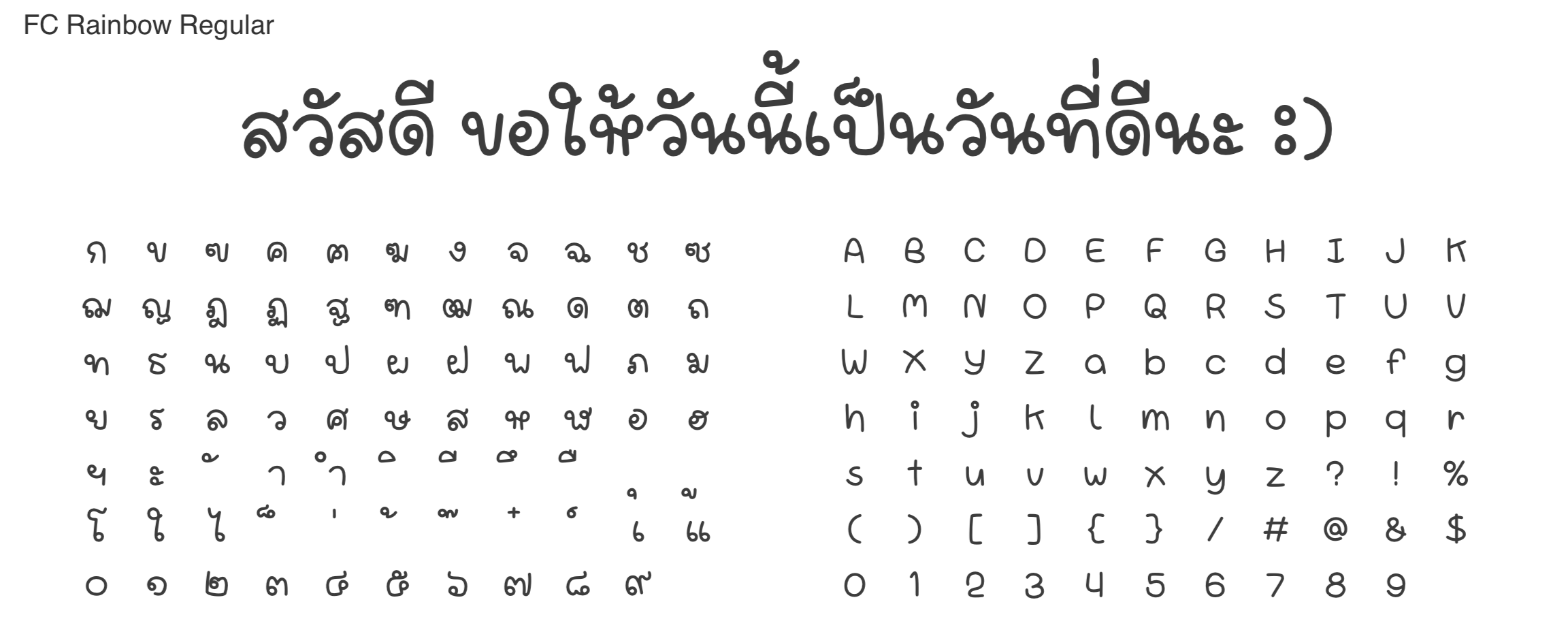
แนะนำ 10 ฟอนต์ไทยสวย ๆ สำหรับใช้งานบนคอมพิวเตอร์, iPhone และ iPad (อัปเดต 2022)
1.เอฟซี เรนโบว์ (FC Rainbow)
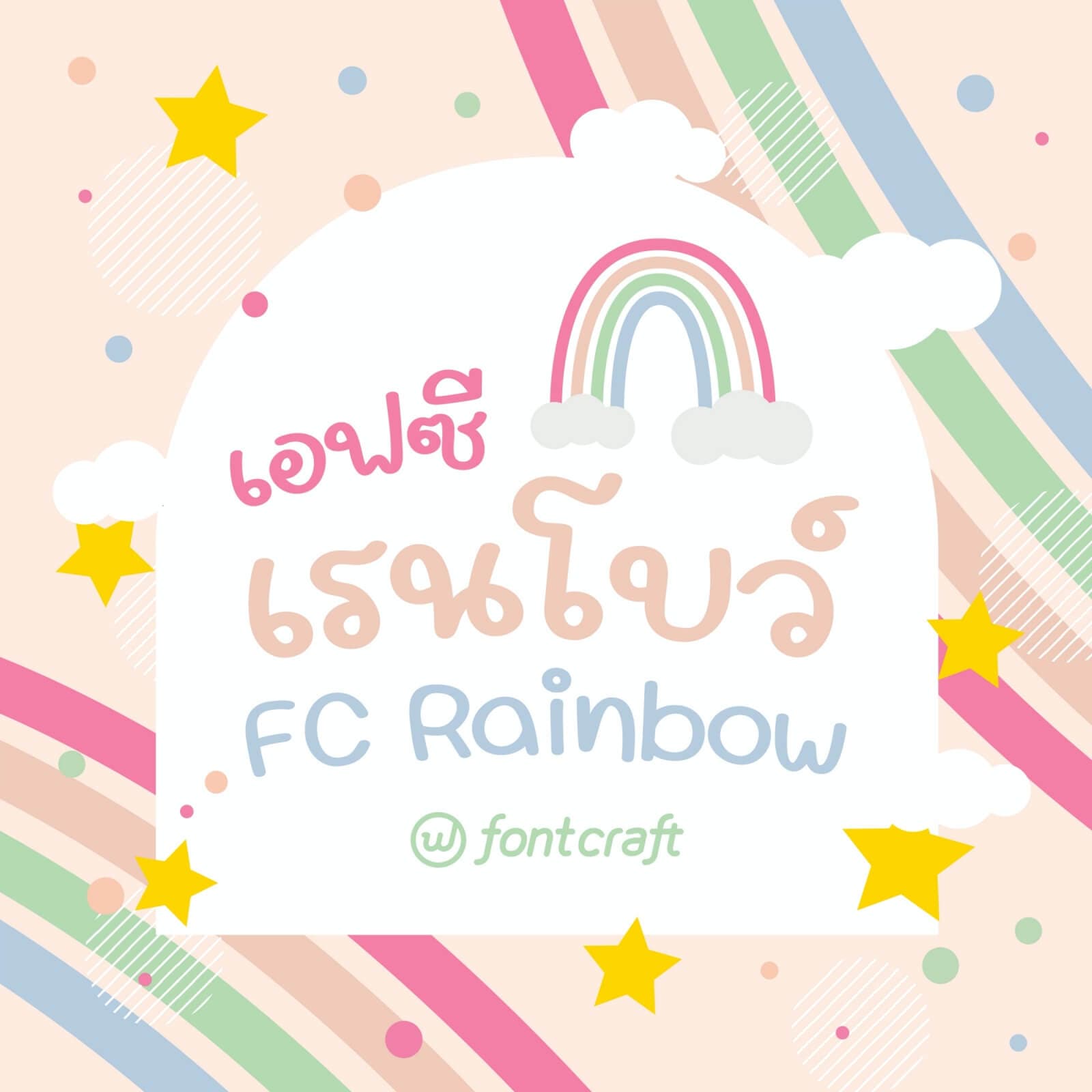
2. เอฟซี ซับเจค ราวด์ (FC Subject Rounded)
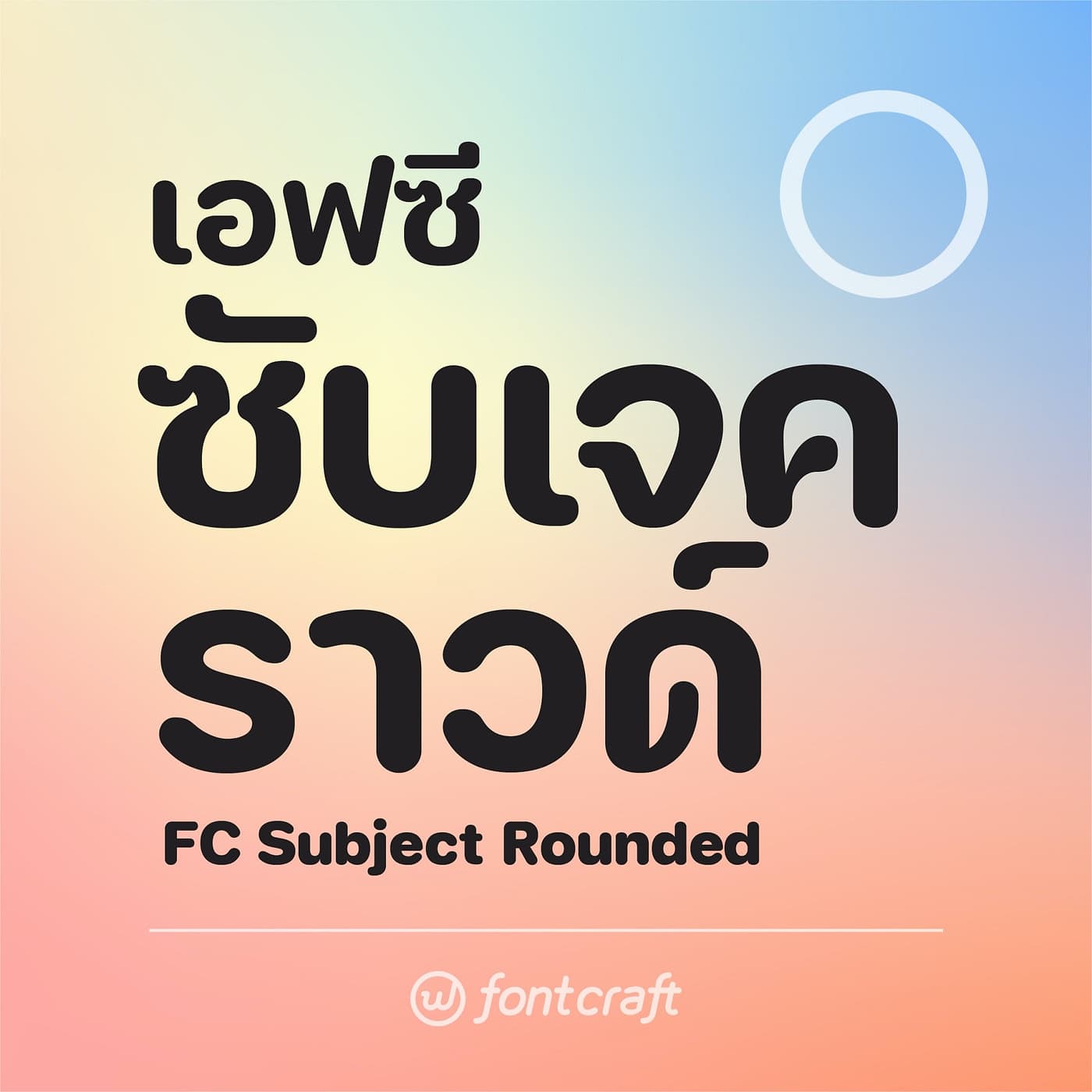
3. เอฟซี เมจิก (FC Magic)
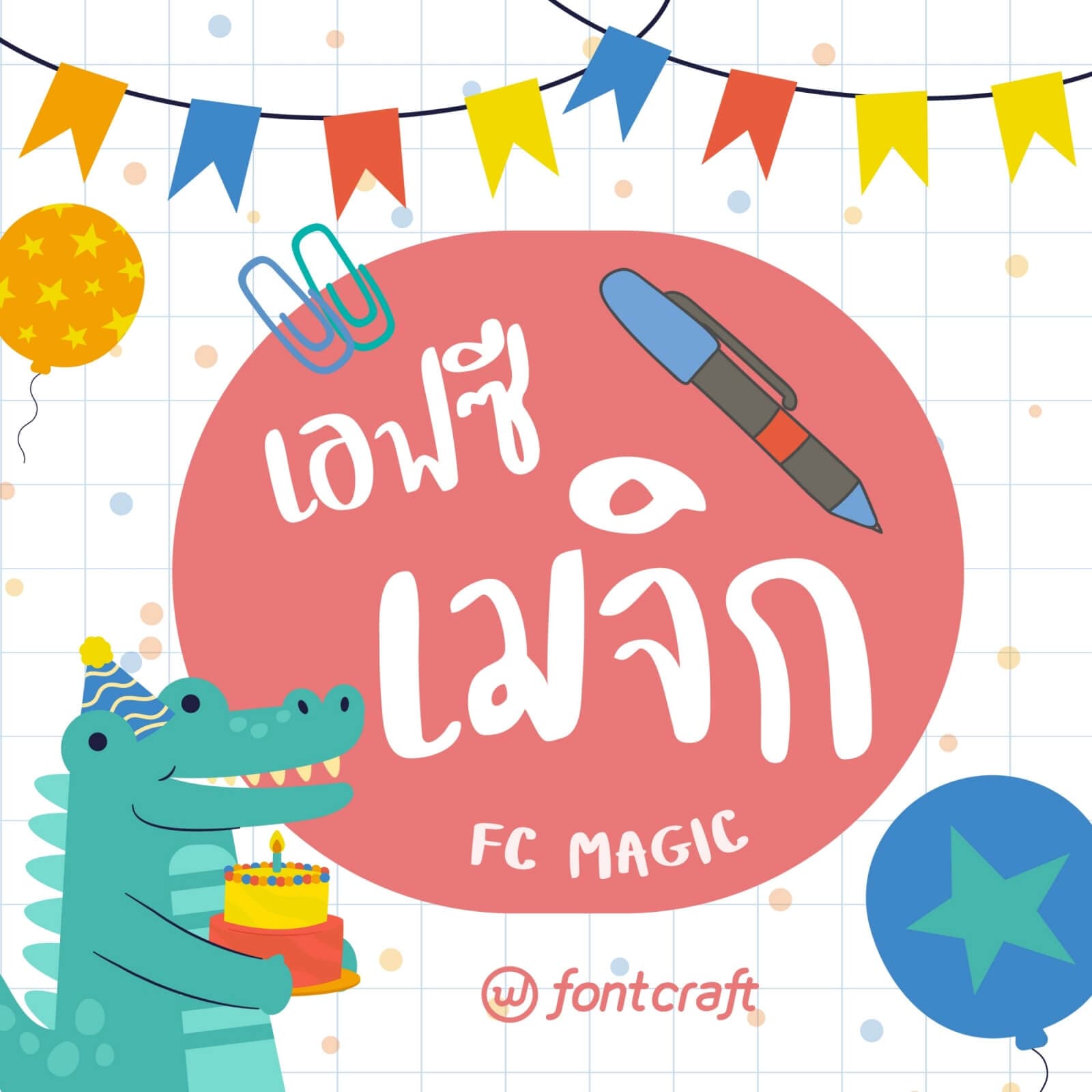
4. เอฟซี แคนดี้ (FC Candy)
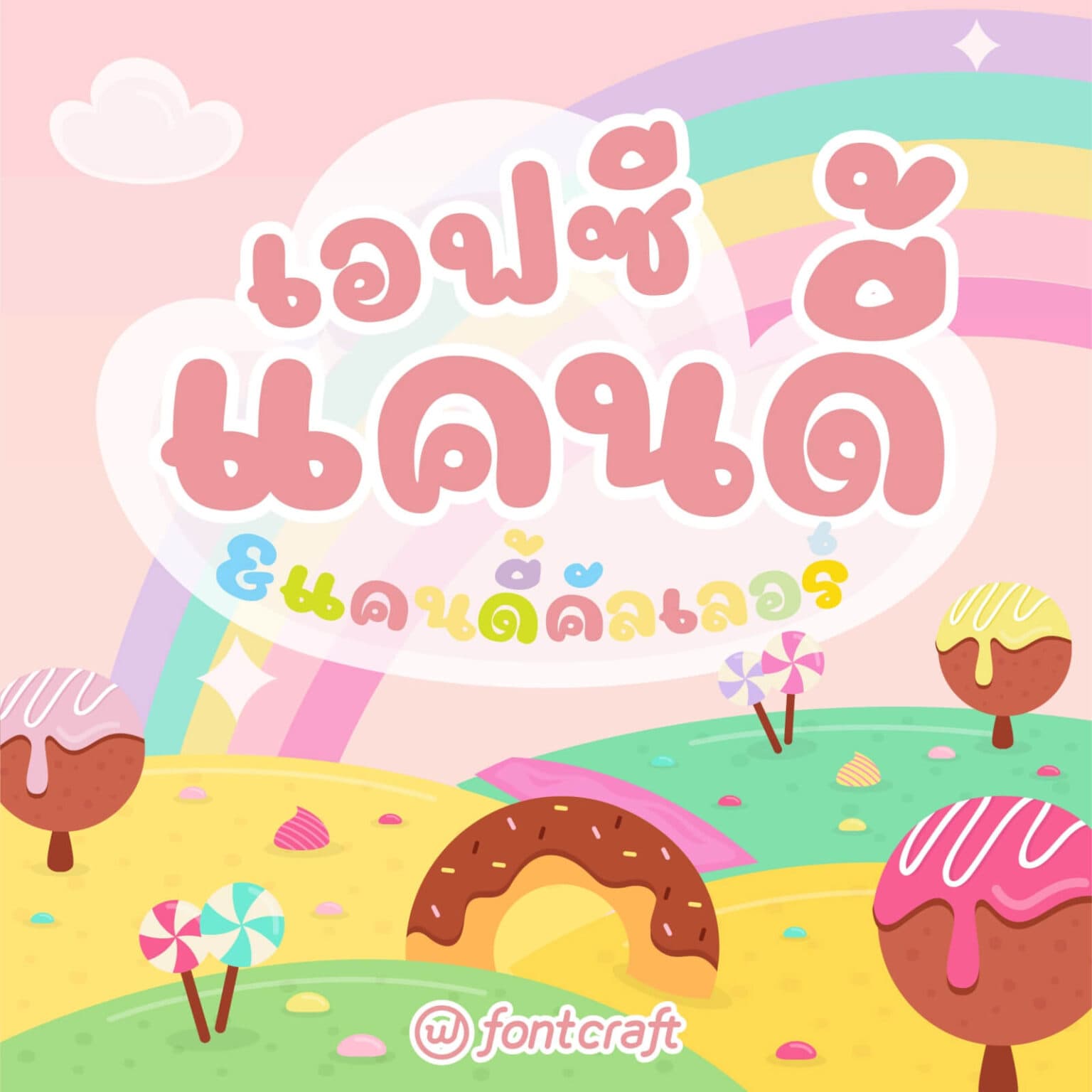
5. เอฟซี มินิมอล (FC Minimal)
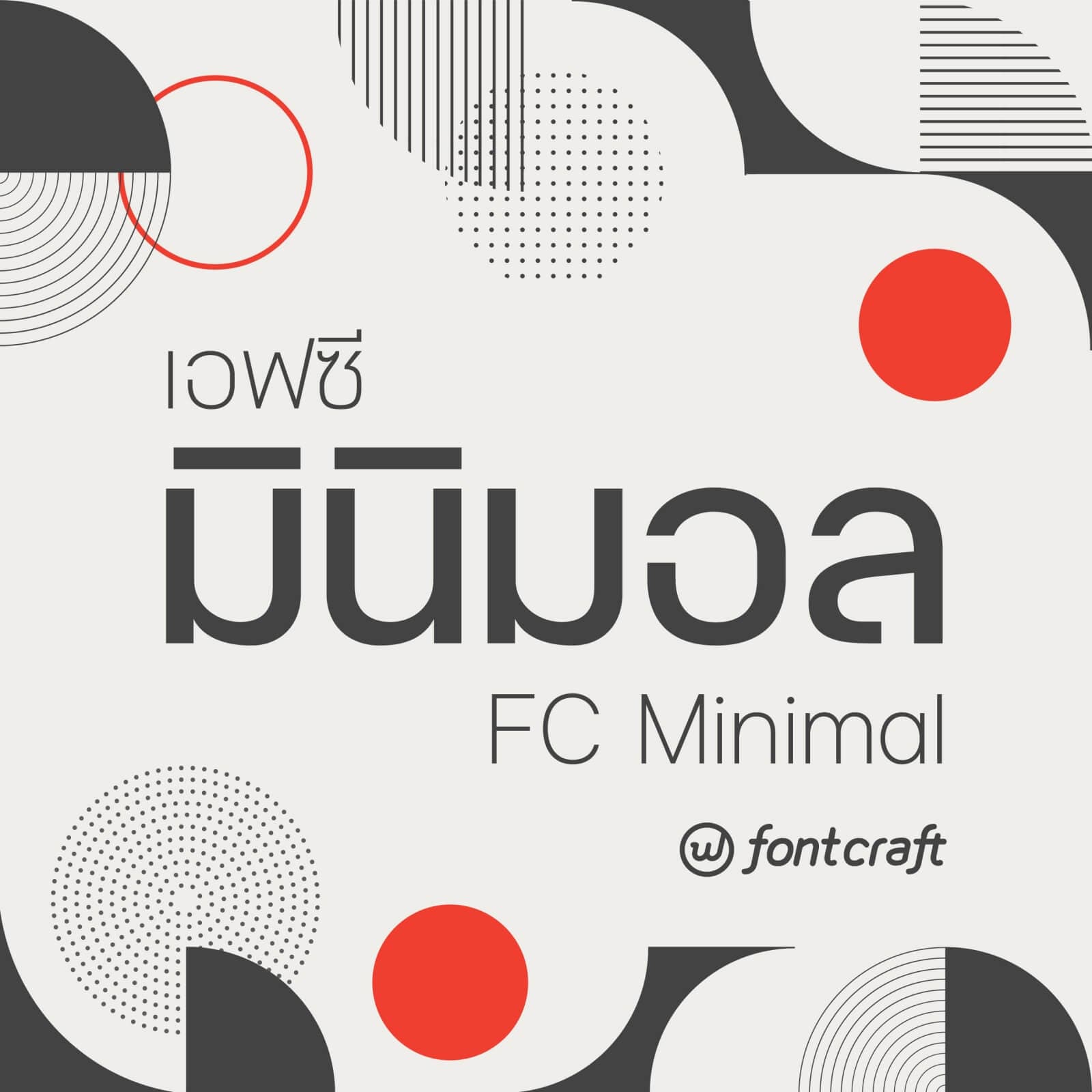
6. เอฟซี พาเลท (FC Palette)
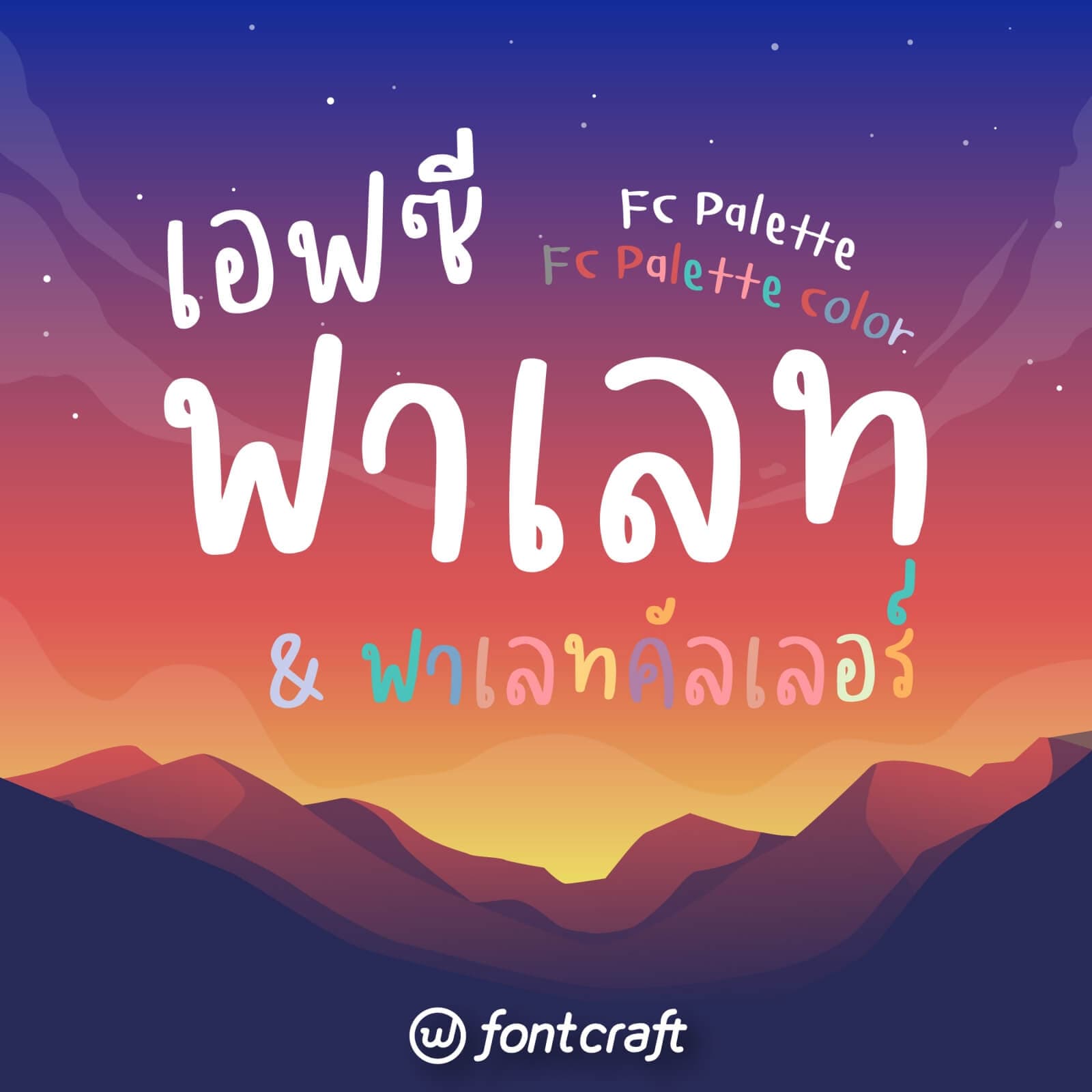
7. เอฟซี มาร์ชเมลโล่ (FC Marshmallow)
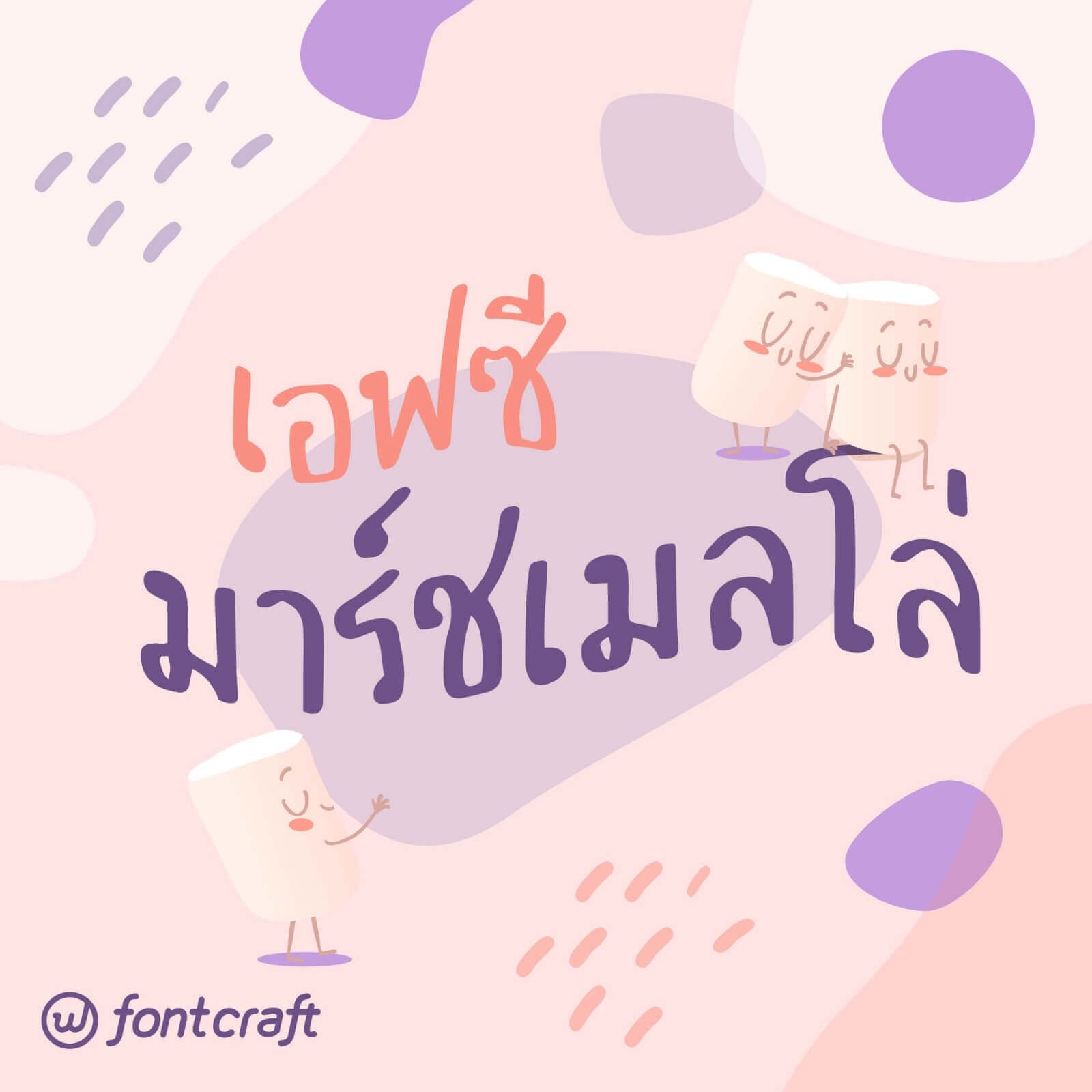
8. เอฟซี มัฟฟิน (FC Muffin)
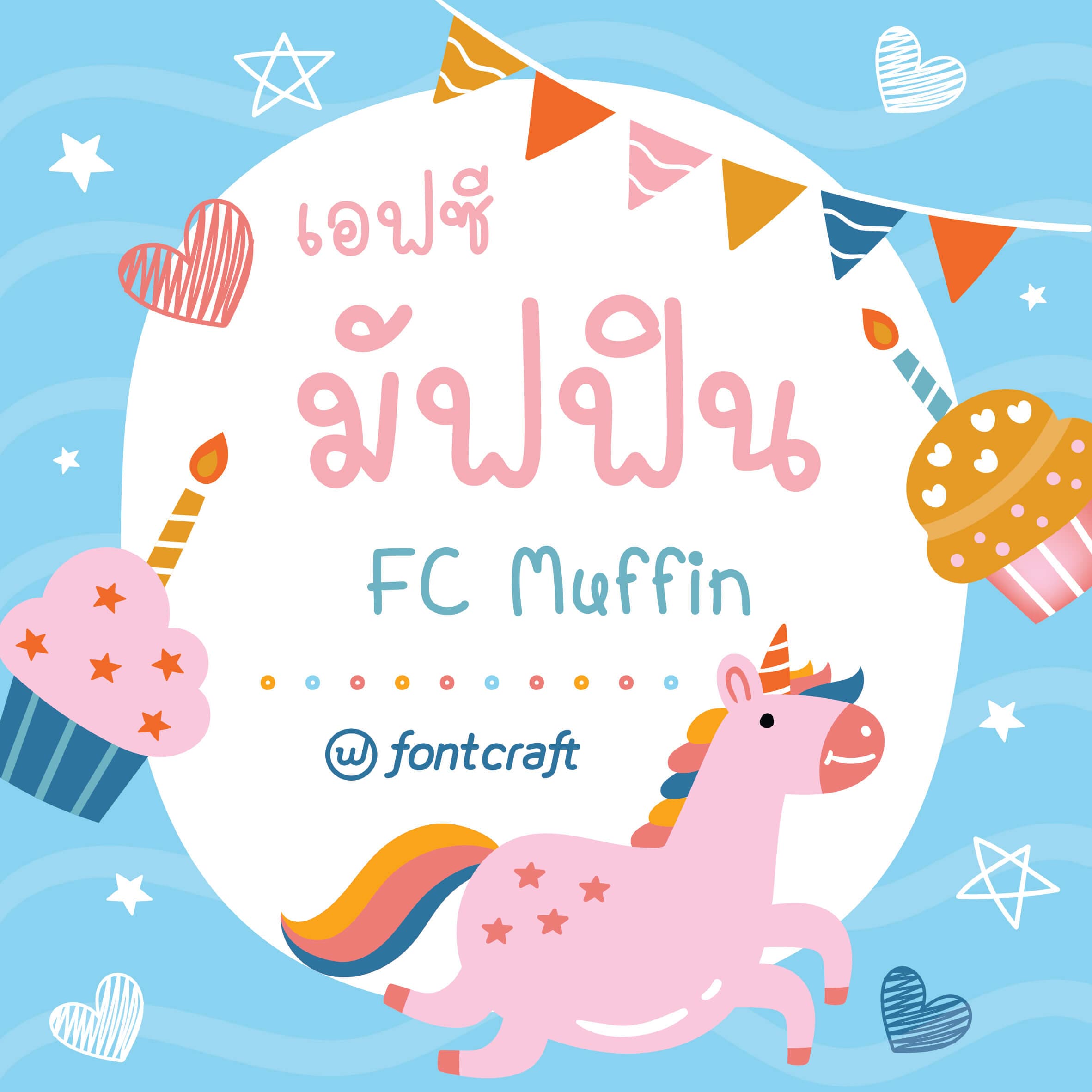
9. ขนมผิง (FC Knomphing)
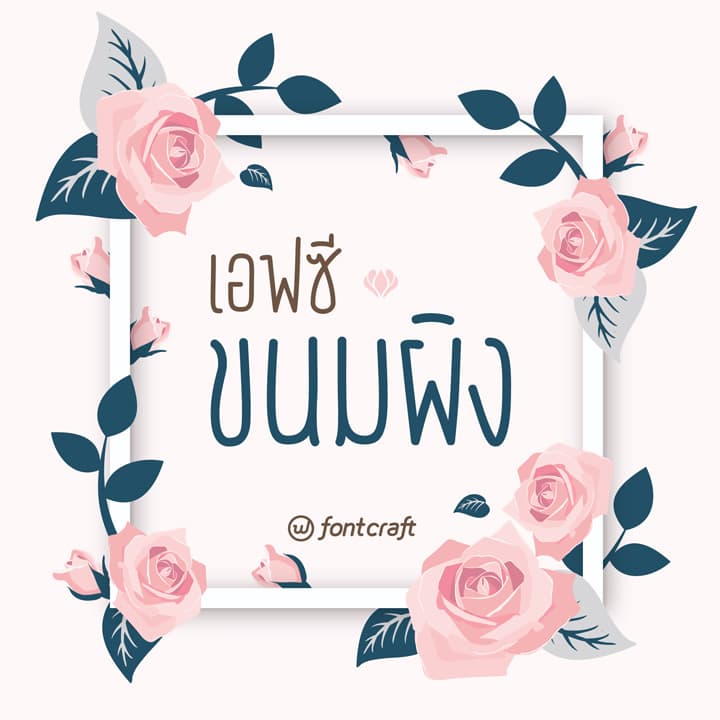
10.ละมุน (FC Lamoon)